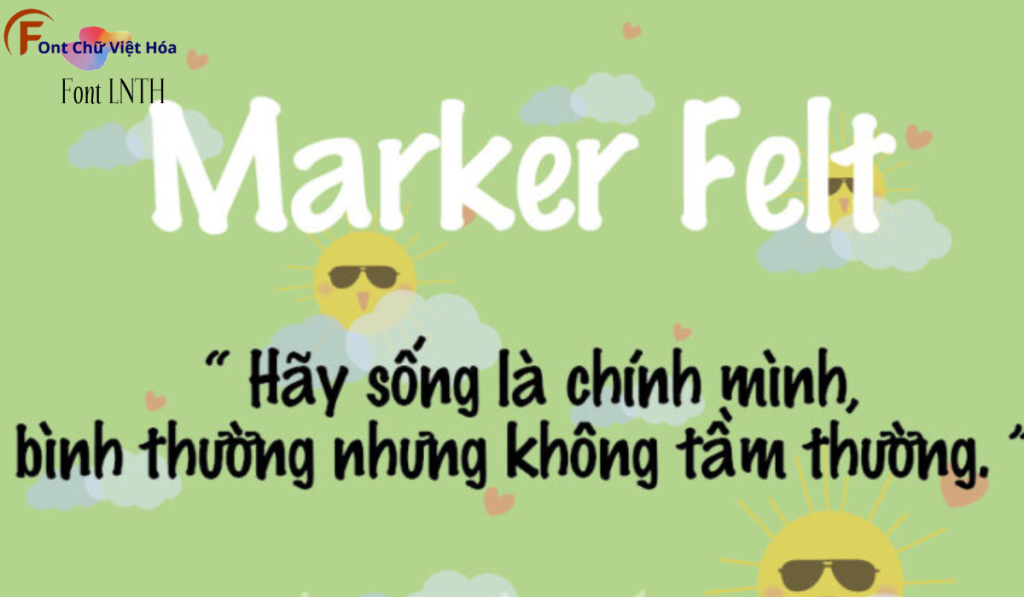
Font LNTH Marker Felt Việt Hóa
Tác giả: LNTH Marker Felt
Bộ Font: LNTH
Phân loại: Cá tính, Độc đáo
Kiểu chữ: Chữ viết tay
Font LNTH Marker Felt Việt Hóa là một font chữ vui nhộn, thuộc bộ LNTH, với thiết kế như nét bút lông. Phong cách của font này phù hợp với các dự án thiết kế cần sự vui tươi và thân thiện, như poster, thiệp mời, hoặc bảng hiệu. Font LNTH Marker Felt Việt Hóa mang đến sự vui nhộn và dễ nhận diện, ứng dụng trong các lĩnh vực sáng tạo. Đặc điểm hình dạng của font bao gồm các nét bút lông mềm mại và tự nhiên, giúp tăng tính thẩm mỹ và sự chú ý. Việc Việt hóa font giúp người dùng dễ dàng sử dụng trong các thiết kế tiếng Việt, mang lại sự tiện lợi và linh hoạt.